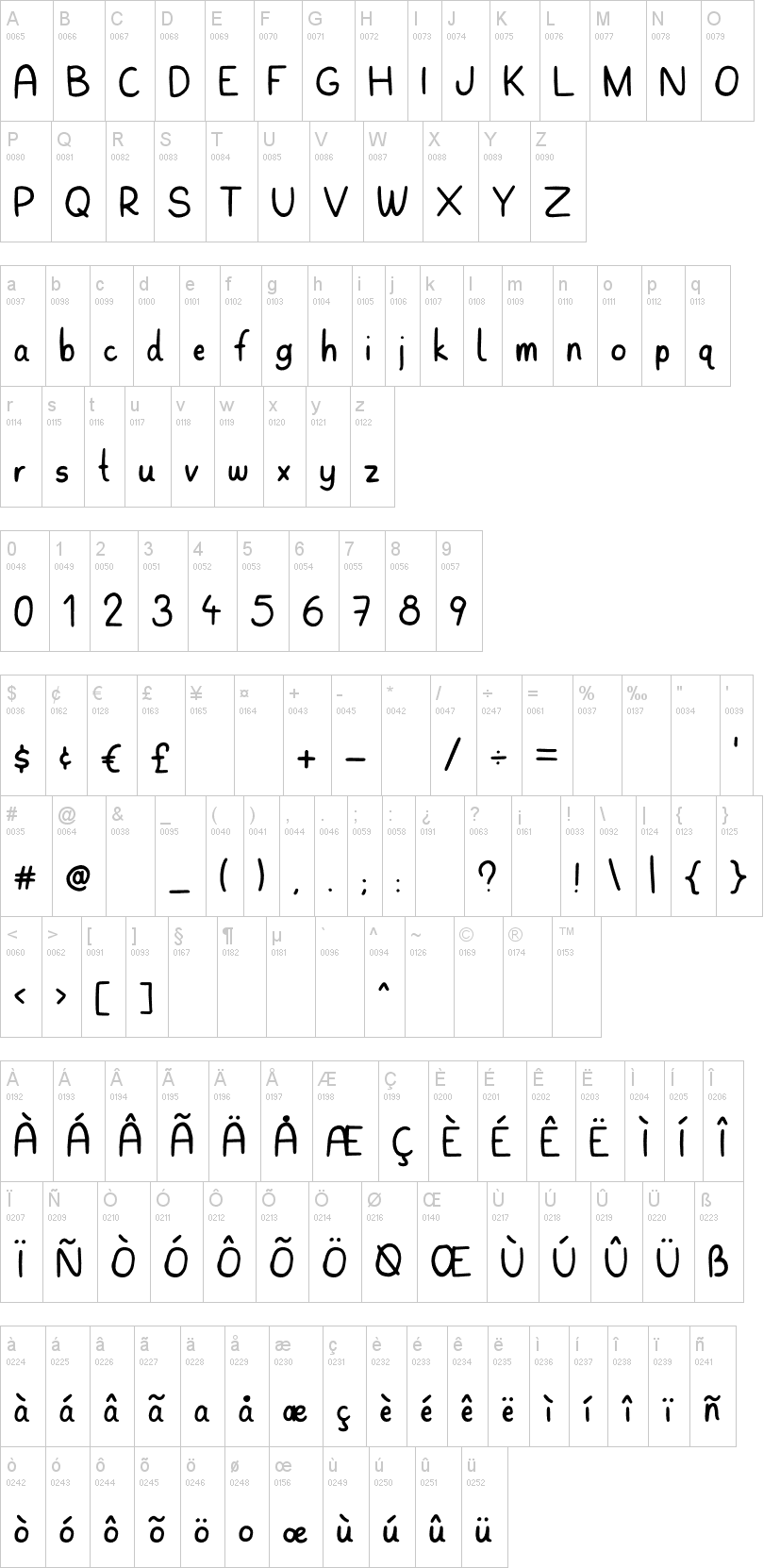
Marbelous
Marbelous字体是一款受到现代科技和经典石材艺术影响的字体。它具有抽象的技术感,但又不失经典的美感。它的字母具有抽象的技术感,而且有着精致的细节,使它具有经典的外观。它有丰富的字重,可以用于创建复杂的设计,也可以用于创建简单的设计。它可以用于创建多种多样的设计,从网页设计到印刷设计,都能发挥它的功效。
Marbelous是一款非常不错的手写艺术字体,具有很好的视觉感,适合于文化类的宣传设计、商业类品牌的广告和产品包装设计以及个性化文字排版等较多场景。